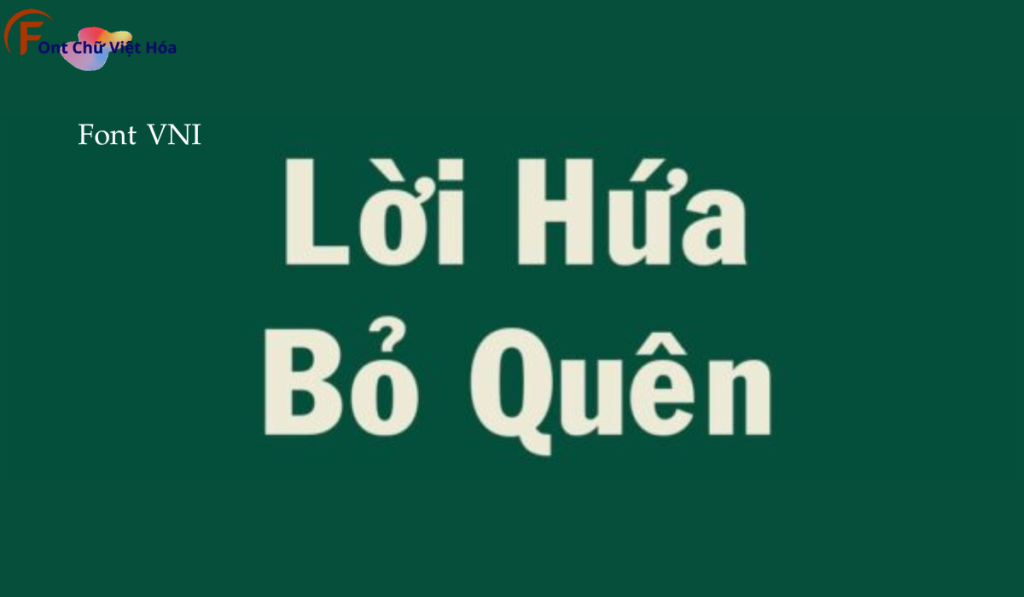
Font VNI Franko Việt Hóa
Tác giả: VNI Franko
Bộ Font: Font VNI
Kiểu chữ: Có chân
Font VNI Franko Việt Hóa, thuộc bộ font VNI, mang phong cách hiện đại và thanh lịch, lý tưởng cho các dự án thiết kế như thiệp mời, bìa sách, và tài liệu văn phòng. Với các nét chữ không chân và độ dày đều đặn, Font VNI Franko Việt Hóa không chỉ dễ đọc mà còn tạo cảm giác chuyên nghiệp và tinh tế. Việc Việt hóa font giúp người dùng dễ dàng tích hợp vào các thiết kế tiếng Việt, mang lại sự tiện lợi và nâng cao tính thẩm mỹ.